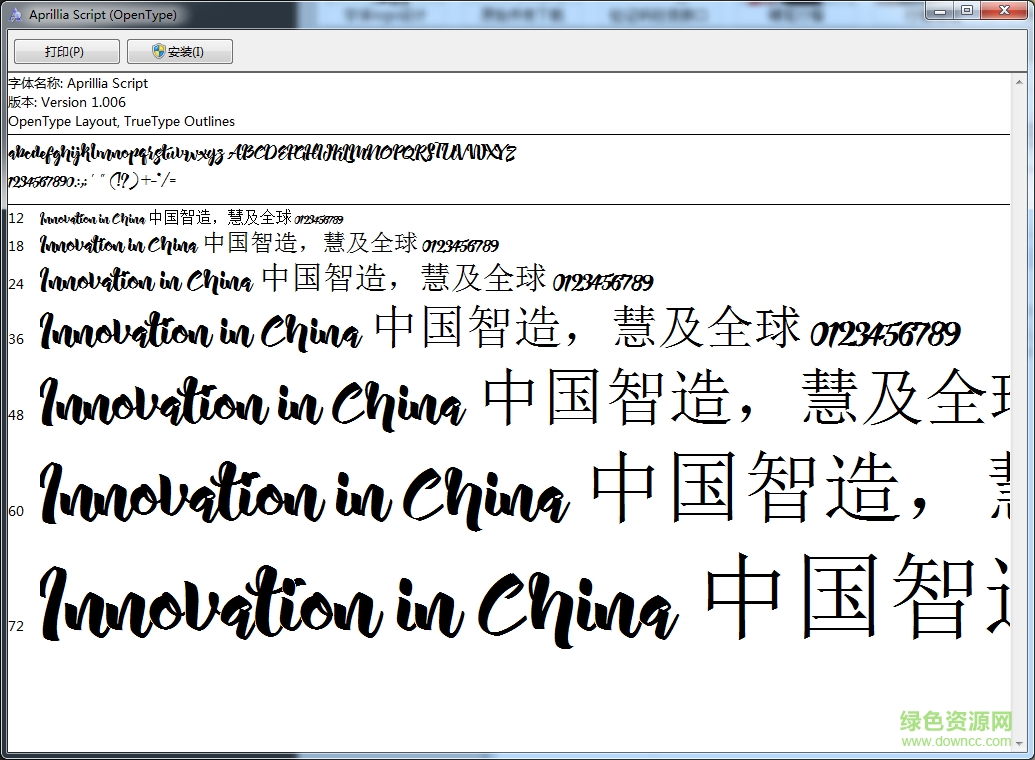
april字體
april字體是一款簡(jiǎn)單實(shí)用的常規(guī)字體,字體彎曲有致極具美感,可直接導(dǎo)入ps中直接使用,使用簡(jiǎn)單時(shí)刻彰顯個(gè)人魅力。快來(lái)綠色資源網(wǎng)下載體驗(yàn)吧!
april字體介紹
無(wú)論漢字,還是拉丁字,任何字體的形成、變化都體現(xiàn)于基本筆形和字形結(jié)構(gòu),基本筆形和字形結(jié)構(gòu)是字體構(gòu)成的本質(zhì)性因素。一種字體構(gòu)成風(fēng)格的形成,完全取決于字體基本筆形規(guī)范化的字體筆調(diào),正因?yàn)橐宰煮w筆調(diào)構(gòu)成字體基本筆形的風(fēng)格定性,才從字體的一筆筆、一畫(huà)畫(huà)中滲透出可見(jiàn)的形象性風(fēng)格。